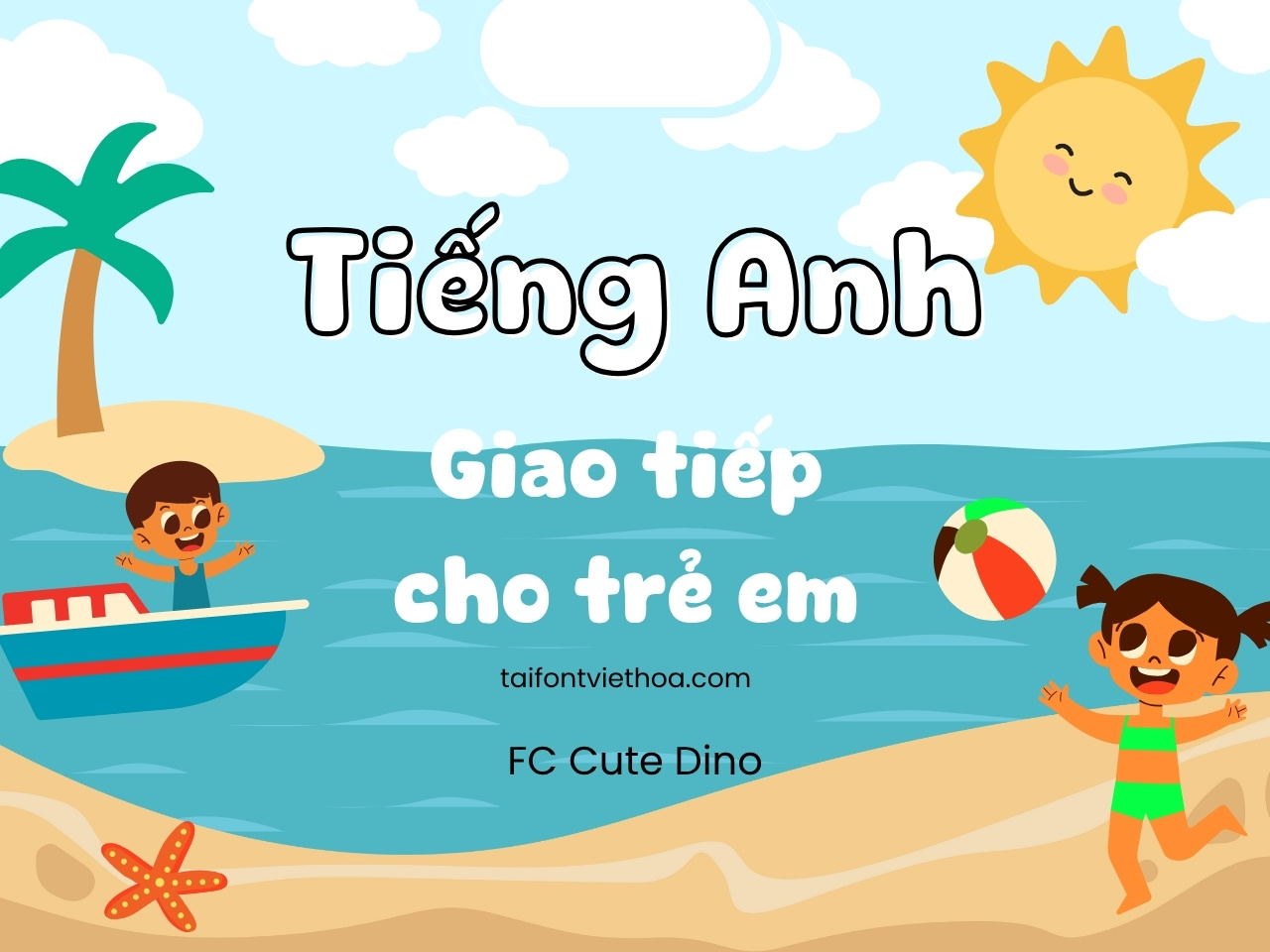
Giới thiệu về font Cute Dino và phiên bản Việt hóa
FC Cute Dino là phiên bản Việt hóa độc lập từ font gốc “Cute Dino” – một kiểu chữ hoạt hình dễ thương được sáng tạo bởi Letterena Studio. Lấy cảm hứng từ thế giới khủng long hoạt hình và nét ngây thơ của tuổi thơ, font mang đến cảm giác vui tươi, thân thiện và tràn đầy năng lượng tích cực. Cute Dino từng xuất hiện phổ biến trên các nền tảng như Creative Fabrica, được ứng dụng nhiều trong thiết kế giáo dục, ấn phẩm cho trẻ em hoặc các sản phẩm giải trí giàu màu sắc.
Khác với phiên bản “1FTV VIP Cute Dino” đã phát hành trước đó, FC Cute Dino là một bản Việt hóa riêng biệt, được thực hiện bởi cộng đồng Font Chuẩn với bộ dấu tiếng Việt được tinh chỉnh cẩn thận, đảm bảo tương thích hoàn toàn với Unicode và vẫn giữ trọn tinh thần ngộ nghĩnh, bo tròn, bay bổng của bản gốc.
Đặc điểm thiết kế ngộ nghĩnh – Gợi mở thế giới tuổi thơ
FC Cute Dino nổi bật với cấu trúc chữ mềm mại, đường nét tròn trịa và các chi tiết bo góc vui mắt. Từng ký tự được cách điệu nhẹ để tạo cảm giác sinh động, giúp trẻ em dễ tiếp cận và ghi nhớ hơn. Bảng chữ in hoa được trình bày đồng đều, không quá cứng nhắc, dễ áp dụng cho tiêu đề hoặc các thiết kế cần nhấn mạnh thông tin.
Font đặc biệt phù hợp với các dự án như: bìa sách thiếu nhi, nhãn mác đồ chơi, giao diện trò chơi giáo dục, banner lớp học, logo trường mầm non hoặc các sự kiện thiếu nhi như Trung Thu, Tết Thiếu Nhi, Giáng sinh. Ngoài ra, FC Cute Dino cũng được nhiều nhà thiết kế sử dụng cho lĩnh vực quảng cáo, đặc biệt là sản phẩm hướng đến trẻ nhỏ và gia đình.